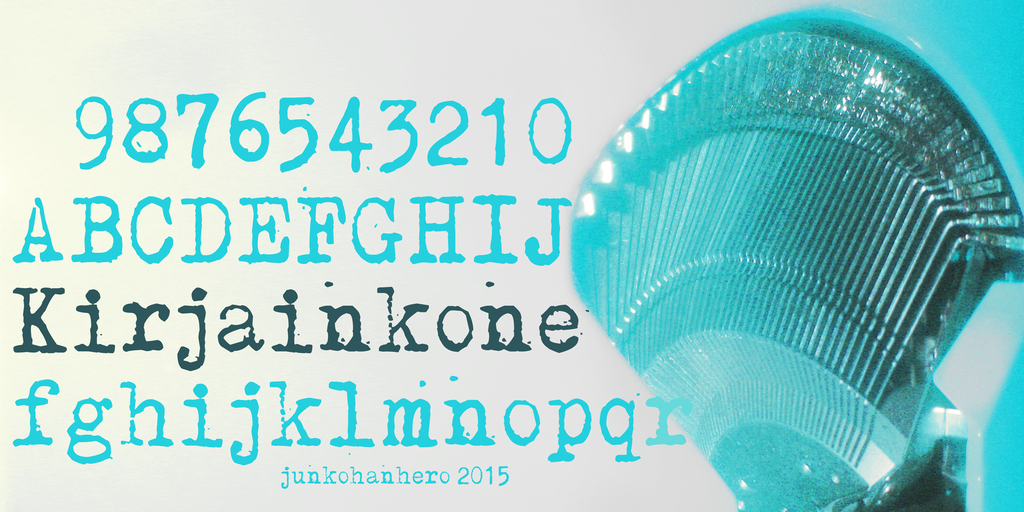
A fonte ‘Kirjainkone’ é uma escolha perfeita para projetos visuais modernos que valorizam a exuberância visual e a simplicidade desejáveis dos typewriters de década de 1900. Desenvolvida pelo designer Hamilton, esta fonte do tipo display oferece um toque vintage com uma aparência limpa e legível. Com destaque para as letras finas e os traços marcantes, ela é perfeita para criar designs chamativos que destacam o texto em qualquer ambiente de design ou layout. Ideal tanto para designers gráficos quanto para aqueles que simplesmente desejam dar um toque diferente aos seus projetos pessoais, a ‘Kirjainkone’ pode ser usada livremente para fins pessoais. Para usar na sua próxima produção comercial, basta entrar em contato com o designer para comprar uma licença de uso comercial. Este processo envolve apenas enviar uma quantia de 15€ ou $20 através da Paypal e depois informar Hamilton por email. A fonte também aceita o pagamento via donate button, localizado ao lado do botão de download. Se você achar que vale a pena dar um pouco mais pela fonte ou simplesmente deseja apoiá-la sem comprometer seu orçamento, pode usar esse método. Essa fonte é perfeita para criar uma sensação única e autêntica em seus projetos visuais, proporcionando um toque de sofisticação que tornará sua peça final ainda mais impecável. Sempre lembrando, a ‘Kirjainkone’ oferece um design de alta qualidade que merecerá cada centavo investido para melhorar o seu projeto.